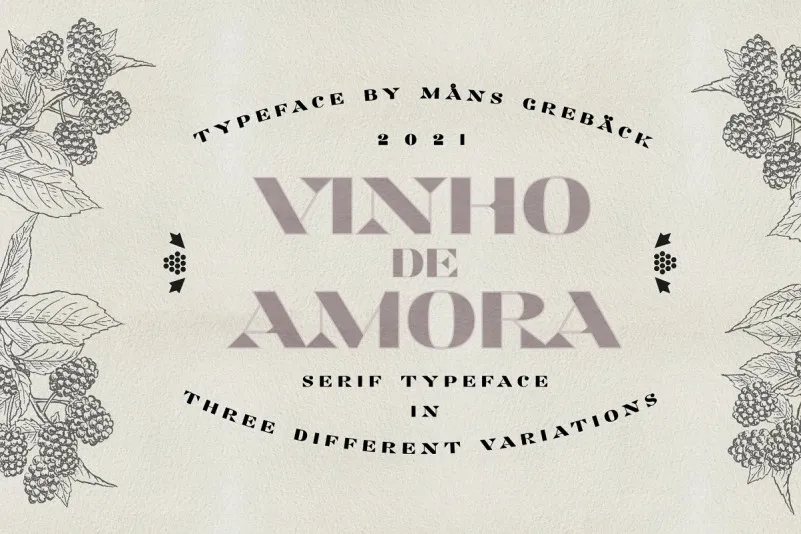
Esta fonte serif é inspirada em vinícolas únicas e ricas em história, incorporando elementos do tipo tipográfico pintado e produção de qualidade genuina. Seu estilo futurista clássico apresenta alternativas únicas que dão um toque agradável à sua escrita. Desenhada por Mans Greback entre 2019 e 2021, essa font é perfeita para quem busca uma grife sofisticada e elegante. Seja para criar materiais impressos ou projetos digitais, a Vinho De Amora Font oferece os detalhes que tornam sua produção ainda mais impressionante. Ideal tanto para uso profissional quanto pessoal, esta fonte é um excelente recurso gráfico para qualquer designer interessado em incorporar elementos únicos e sofisticados.